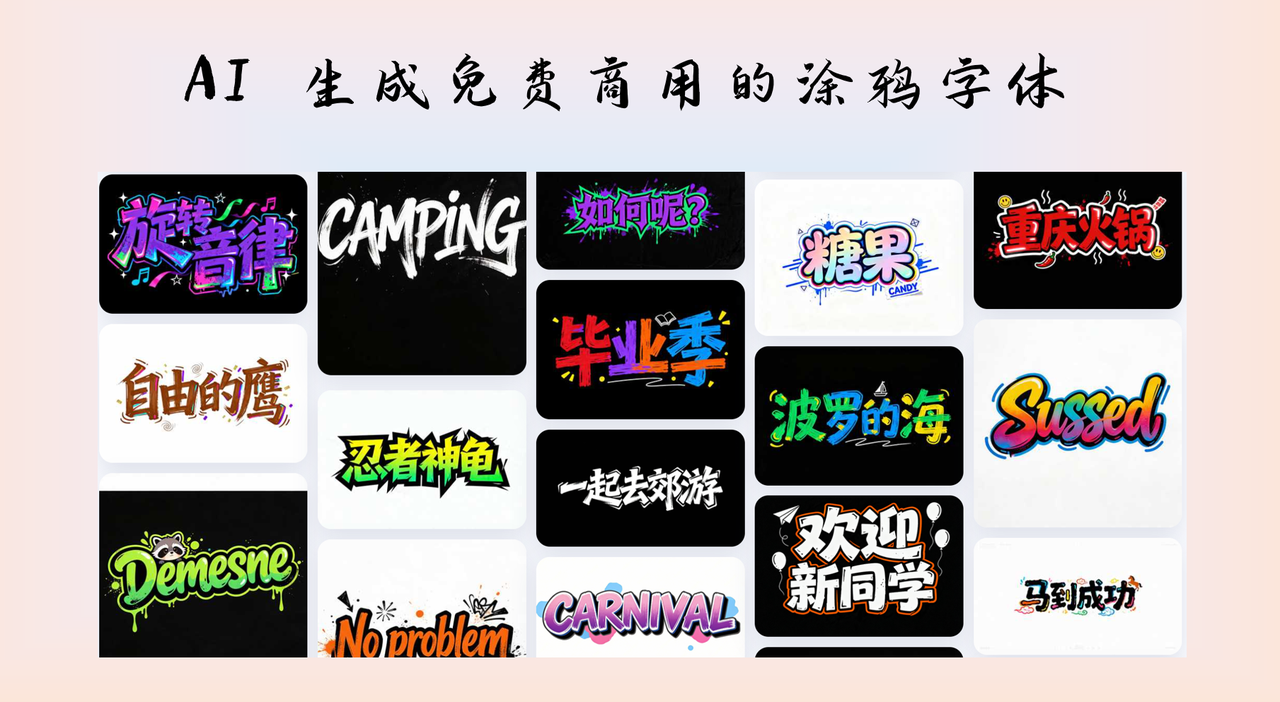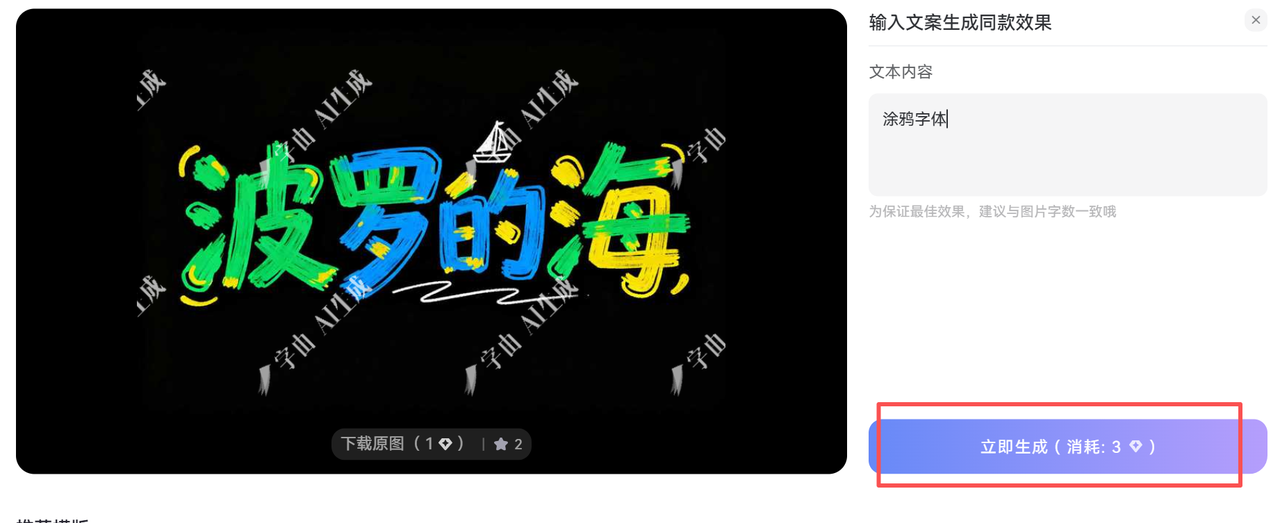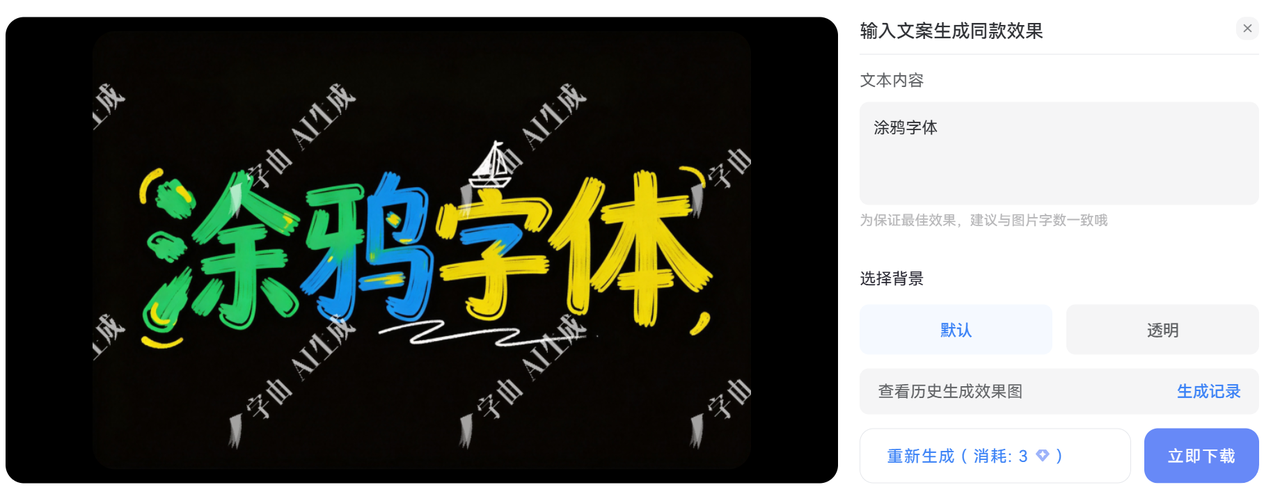
涂鸦字体去哪下载?AI 一键生成免费商用的涂鸦字体
今天我的经验分享给你,让你用AI生成这些好看的涂鸦字体,给作品增添更多活力和创意。
什么是涂鸦字体
这类字体通常带有手写感、不规则笔触,看起来像是用喷漆罐或马克笔随手涂画出来的效果。它们适合街头风格、潮流品牌、音乐活动海报、儿童产品包装等需要展现个性和年轻态度的场景。
我自己最常用涂鸦字体的地方是做促销海报和品牌宣传物料,用上之后整个画面立刻就"活"了起来,比普通字体更能抓住眼球。
字由 AI 字体:免费商用的涂鸦字体生成神器
我要重点推荐的第一个工具是字由的 AI 字体设计功能。
字由本身是一个字体管理工具,我用了快两年了。最近他们上线了 AI 字体设计功能,我试用后发现真的很实用。
如何生成涂鸦字体
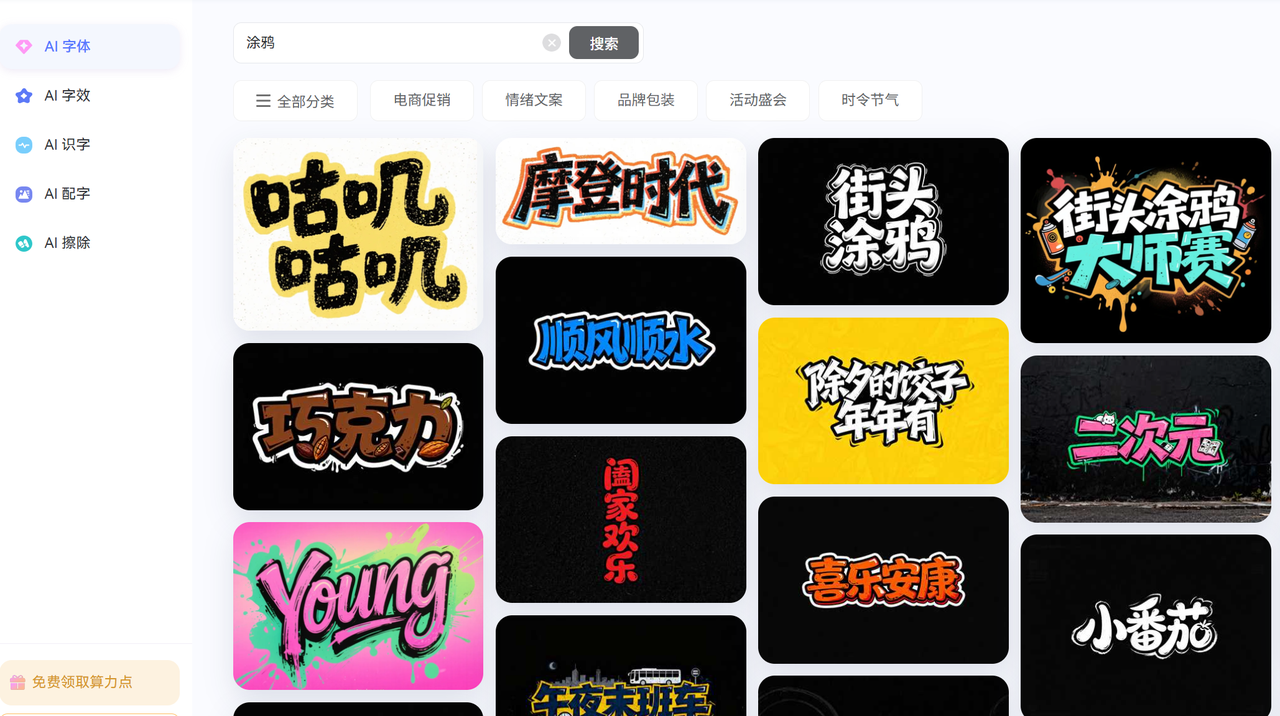
- 筛选符合你需求的涂鸦字体,涂鸦字体模板非常丰富,可以多试几款
- 输入自己的文字,点击一键生成
我常用的几款涂鸦字体
Young
年轻活力的一款涂鸦字体,非常适合学生群体
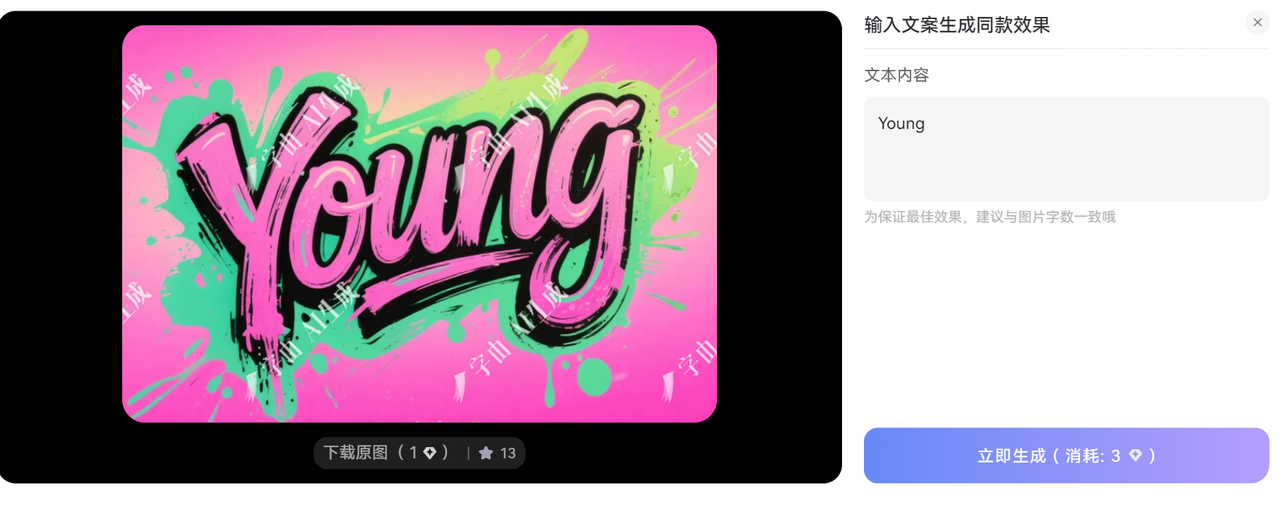
如何呢?
如何呢,又能怎,比较有梗的一款涂鸦字体,比较适合一些综艺节目
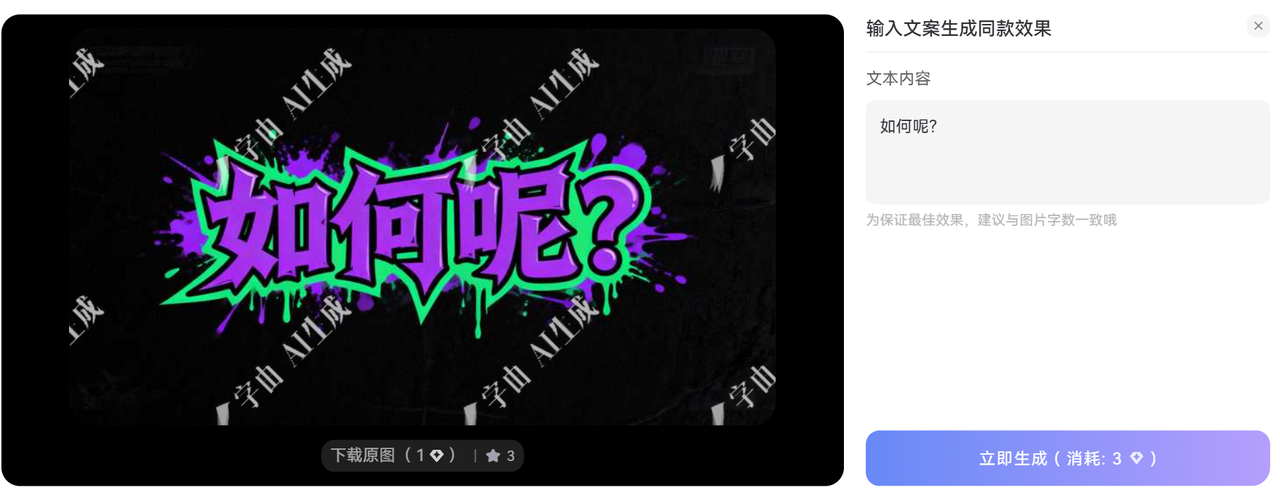
热爱生活
音乐节、旅行等场景
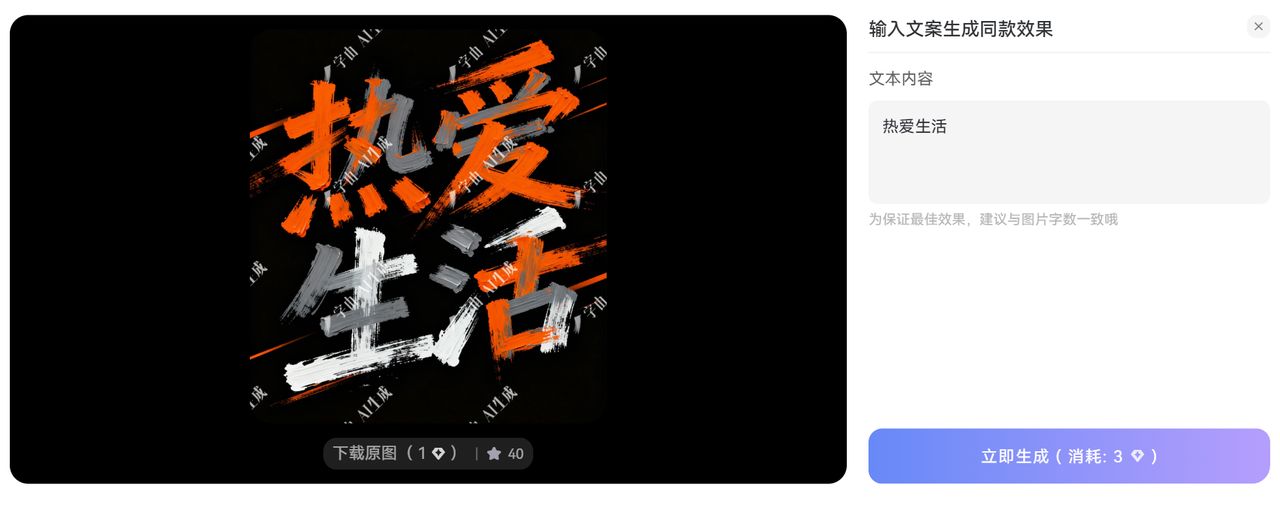
写在最后
找免费商用的涂鸦字体其实没那么难,对于这种艺术设计字体,我现在比较常使用 AI 来生成,然后再对细节进行修改,效率非常的高。建议大家也去试试 AI 生成涂鸦字体,同时还有其它多款的字体模板。包含国风、像素、霓虹等风格。